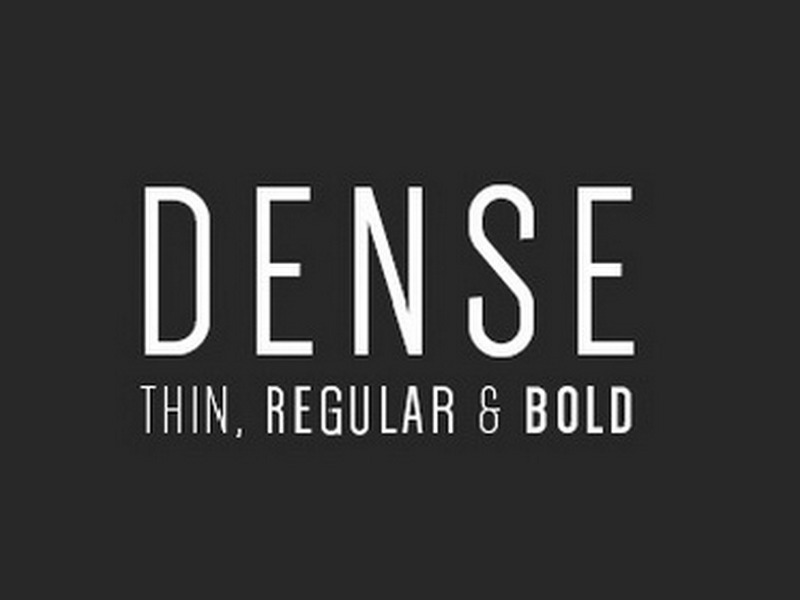
Типографика в веб дизайне. Основные понятия и правила
Статья будет полезна для молодых дизайнеров, для людей, которые начали свое дело и впервые создают сайт, для всех, кто работает с визуальным контентом и наполнением сайтов.
Типографика в вебе — это правила оформления текста сайта с целью донесения информации до аудитории в легчайшем для чтения и восприятия форме. Формат оформления влияет на показатели времени проведенного пользователем на сайте, совершение целевой действия и общего впечатления от сайта. Чтобы разобраться в основных правилах и форматах — читайте статью ниже.
# 1 Разбираемся в основных понятиях
Как сделать так, чтобы текст на странице читали? С развитием интернет — пространства увеличился и объем информации, поэтому мы постепенно научились фильтровать информацию, выделять нужное.
Текст — главный элемент на странице, именно он подталкивает пользователя к действию.
Для создания понятного и читабельного текста, в котором легко ориентироваться, мы обратимся к правилам типографики.
Неважно насколько полезна информация в текстовом блоке, если текст неправильно оформлен — он останется без внимания.
Для начала разберемся с основными понятиями, чтобы легче усвоить дальнейшие правила.
- Шрифты и гарнитура
Шрифт — это набор малых и больших символов, знаков препинания, цифр и спецсимволов одного размера и толщины для отдельной гарнитуры.
Гарнитура — это «комплект» шрифтов, имеющих общие стилевые признаки и принципы построения знаков.
Коротко разберемся с видами гарнитур:
Лучший вариант для веб-страницы — использовать гротескные гарнитуры, они проще для визуального восприятия, четкие и понятные.
В ситуациях, когда требуется другая ширина символов, не стоит растягивать или сжимать шрифт вручную, существуют специально разработанные варианты шрифтов:
- Кегль
Кегль — определяет плоскость размещения знаков по высоте — от нижней точки буквы «р» до верхней точки буквы «б».
В печатных изданиях размеры шрифтов измеряются в пунктах (pt), а на экране — в пикселях (px). Соотношение размеров вычисляется по формуле:
12 пунктов (pt) × (96/72) = 16 пикселей (px)
Оптимальный кегль для сайтов — 16–20 px (для компьютеров) и 14–18 px (для телефонов), а для печатных изделий — 10–12 pt.
- Насыщенность или толщина
Насыщенность или толщина — определяется изменением толщины основных и соединительных штрихов. В пределах одной гарнитуры насыщенность может изменяться от тончайшего до самого толстого и описывается словами (Thin — Black) или числовыми значениями (100–900).
- Контрастность
Контрастность — отношение толщины основных и соединительных штрихов. Контрастность может изменяться от шрифтов без контраста (1: 1) до шрифтов с высоким контрастом (более 3: 1).
- Трекинг и кернинг
Трекинг — это равномерное изменение расстояний между символами во всем текстовом блоке.
В словах, набранных крупным кеглем, следует уменьшить расстояния между буквами, так слова в строке становятся целостными. Трекинг в тексте малых кеглей нужно увеличить, чтобы облегчить визуальное восприятие текста.
Кернинг — корректировка расстояния между отдельной парой знаков. Современные шрифты уже имеют налаженный кернинг, поэтому нет нужды кернинг отдельных букв. Кернинг настраивают в графическом дизайне и при верстке печатных изделий.
- Х-высота
Высота от основания букв, которая определяется по букве х (икс). Для текстов на сайте используют большую X-высоту, для повышения разборчивости букв малых кеглей.
- Интерлиньяж и межстрочный интервал
Интерлиньяж — расстояние между базовыми линиями соседних строк в тексте.
Межстрочный интервал — расстояние от базовой линии до верхней части строчных на следующей строке.
Для текстов на сайте, размеры интерлиньяжа в абзацах — 120–170%. Обычно, интерлиньяж подбирается дизайнером на глаз, но рекомендуемый интерлиньяж — 150%, в этом случае строки не распадаются, но хорошо отделены, а текст остается читаемым.
В заголовках часто используется отрицательный интерлиньяж — расстояние между строками меньше, чем высота букв. В этом случае заголовок становится целостным блоком и не распадается, при этом заголовки делают короткими, чтобы не заставлять читателя «бегать» глазами по экрану.
# 2 Правильная типографика
- Базовое правило типографики
Не важно, сколько правил типографики вы уже изучили, существует одно базовое правило, которое гарантированно улучшит ваши работы:
Наиболее понятным примером этого правила является ряд размеров:
Апрош ≤ Пробел ≤ Кегль ≤ Интерлиньяж ≤Отбивки абзаца ≤ Расстояние от края
Каждый следующий размер в цепи — больше предыдущего.
Это позволяет, пользуясь одним базовым правилом, сразу повысить читабельность текста, воздушность, понятность, улучшить визуальное восприятие полотна текста.
- Заголовок
Заголовок — важнейший строку текста, кратко описывает информацию в следующих абзацах и подталкивает читать дальше именно тот абзац, где находится нужная информация.
Дэвид Огилви, величайший маркетолог современности, утверждал, что в рекламном тексте никогда не следует использовать реверсивный шрифт. Колин Уилдон, редактор крупнейшего в Австралии автомобильного ресурса, решил проверить эту теорию. Полученные им результаты поразительны:
- черный текст на белом фоне: 70% хорошо, 19% удовлетворительно, 11% плохо
- белый текст на черном фоне: 0% хорошо, 12% удовлетворительно, 88% плохо
- белый текст на фиолетовом фоне: 2% хорошо, 16% удовлетворительно, 82% плохо
- белый текст на синем фоне: 0% хорошо, 4% удовлетворительно, 96% плохо